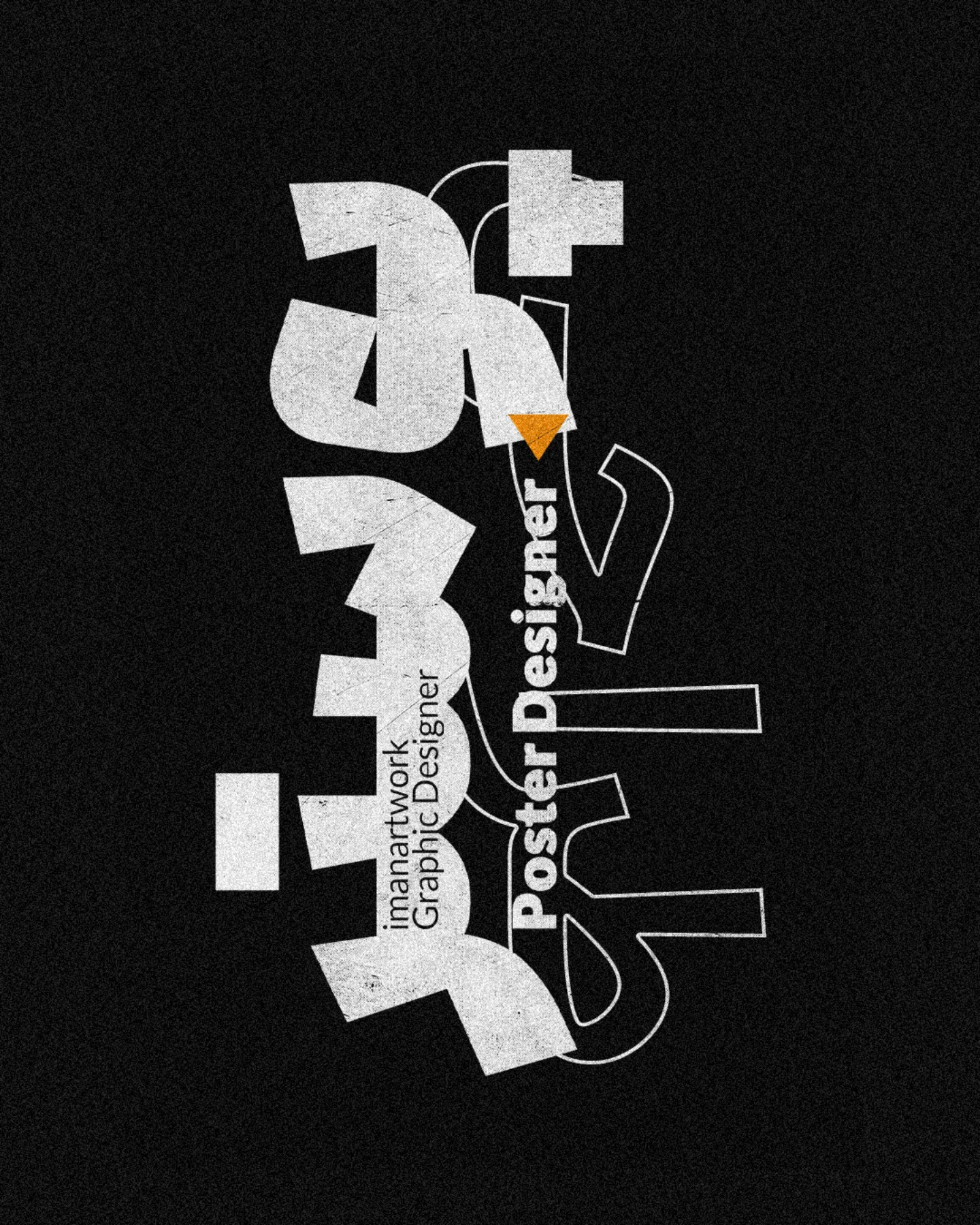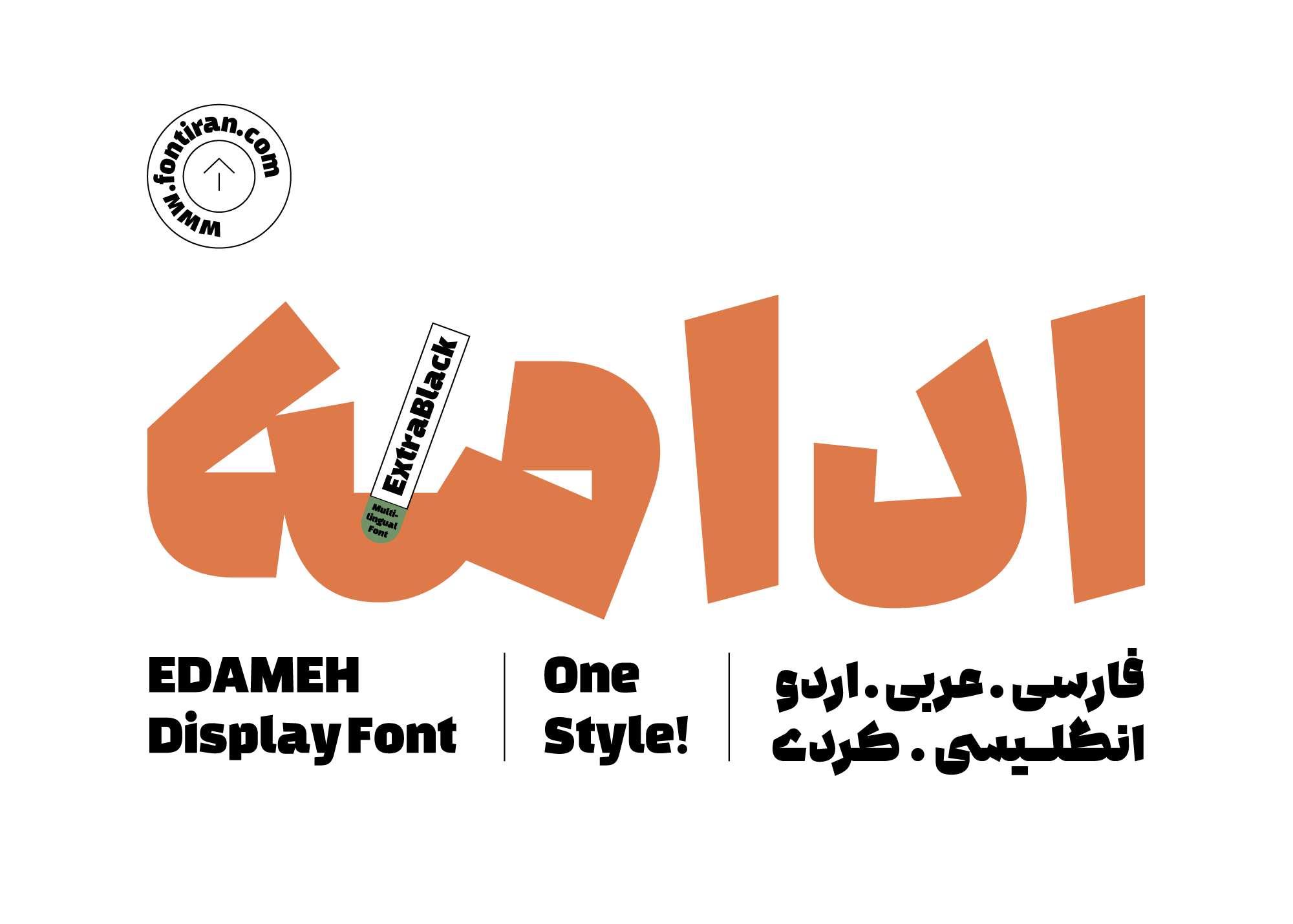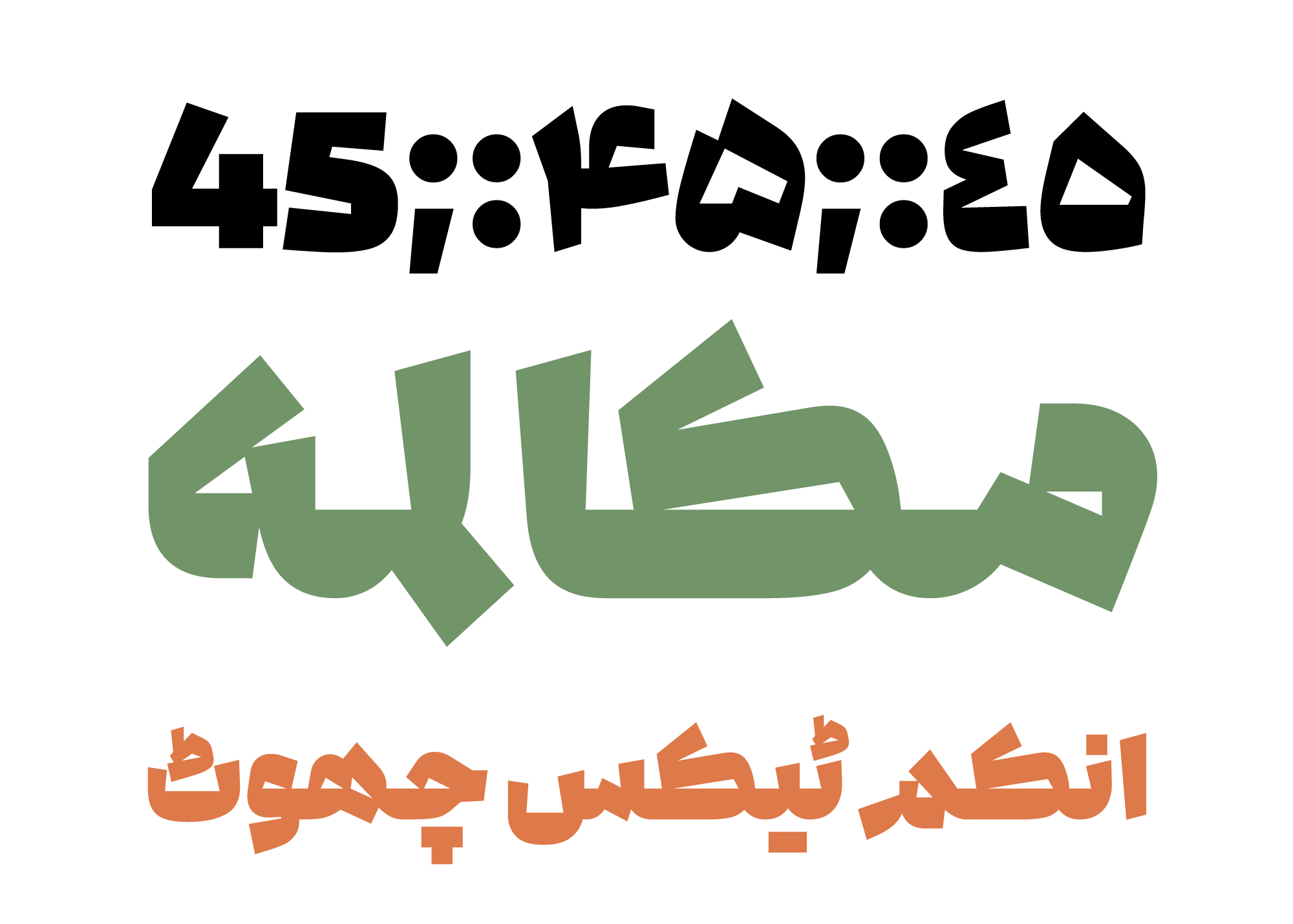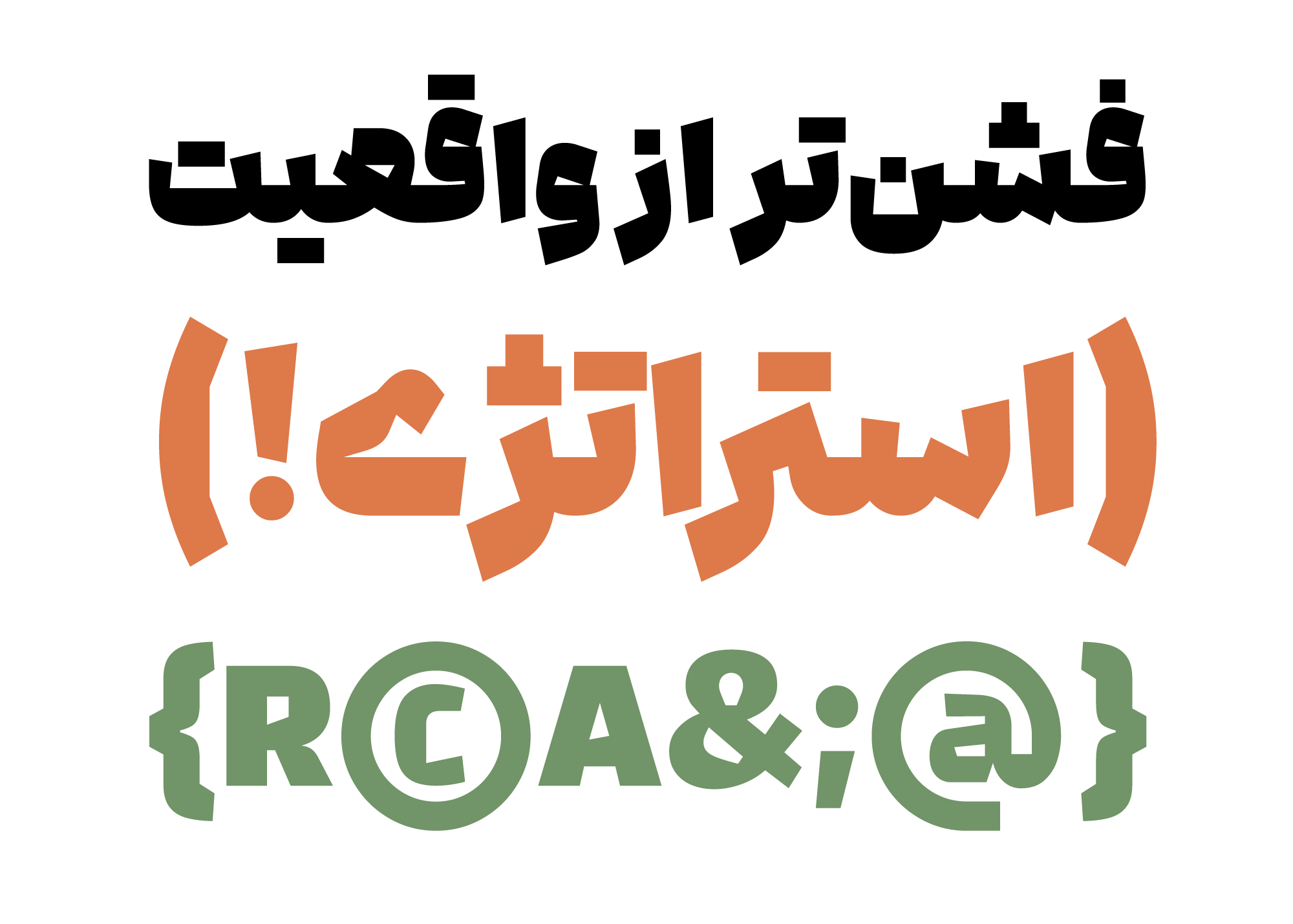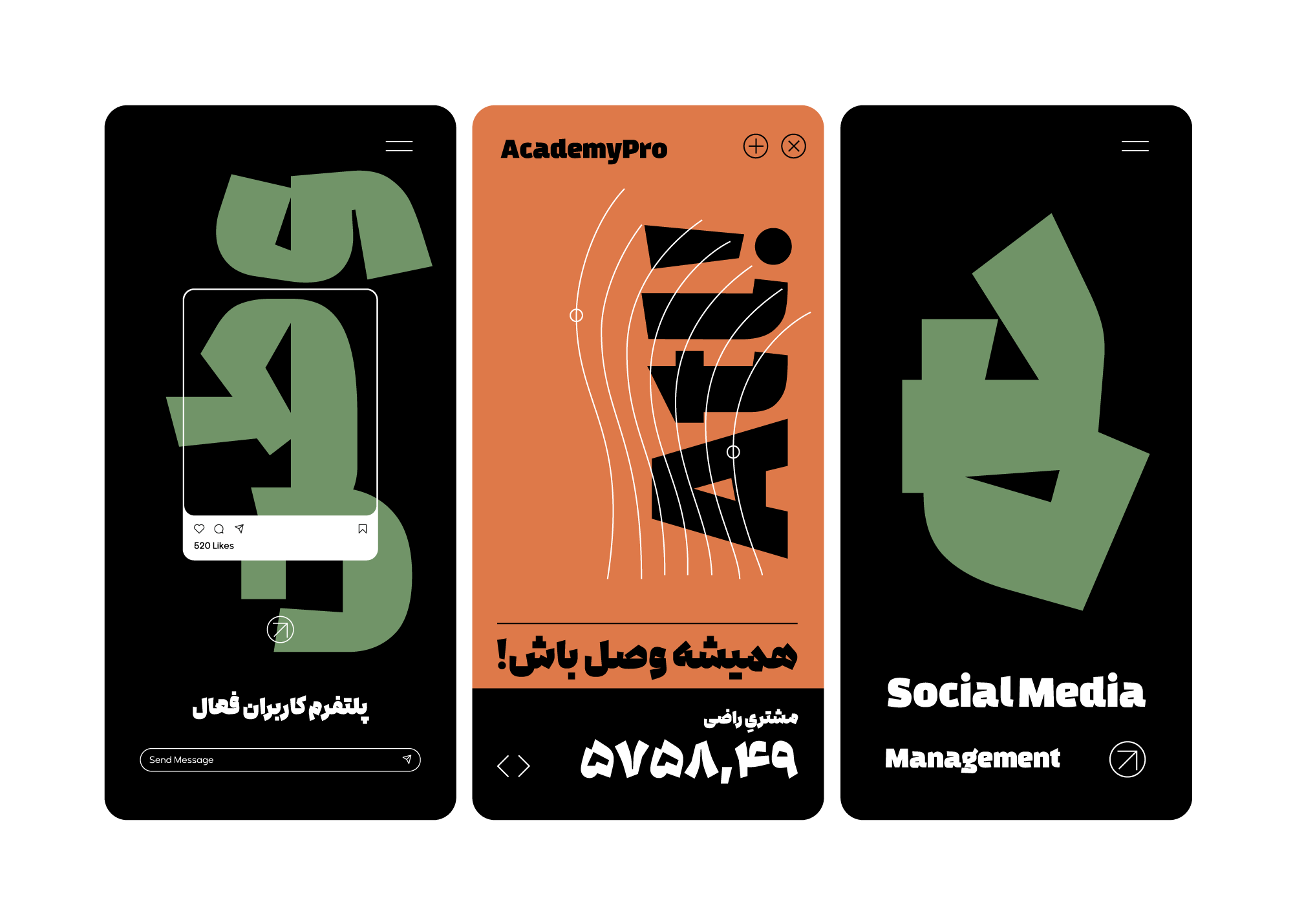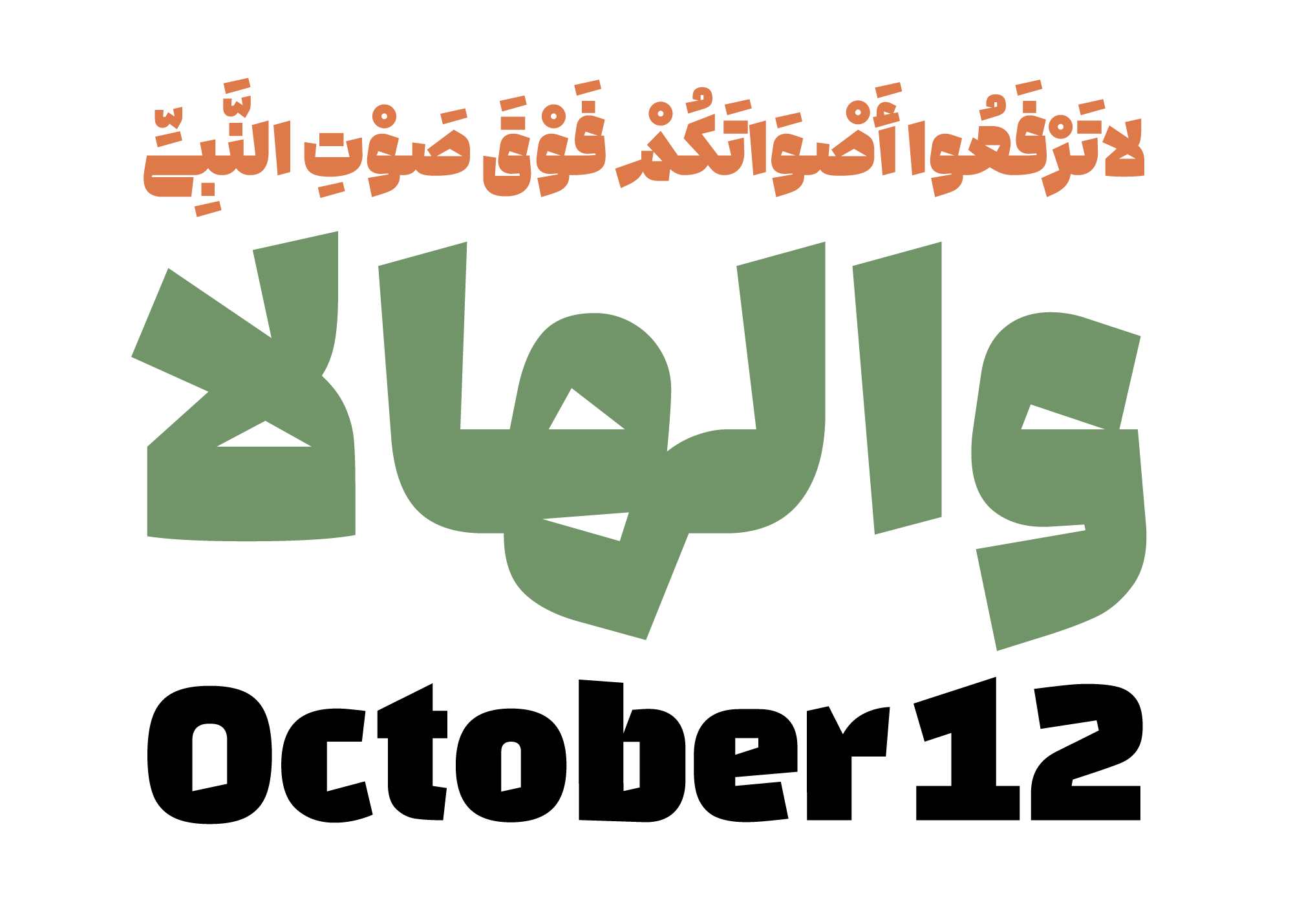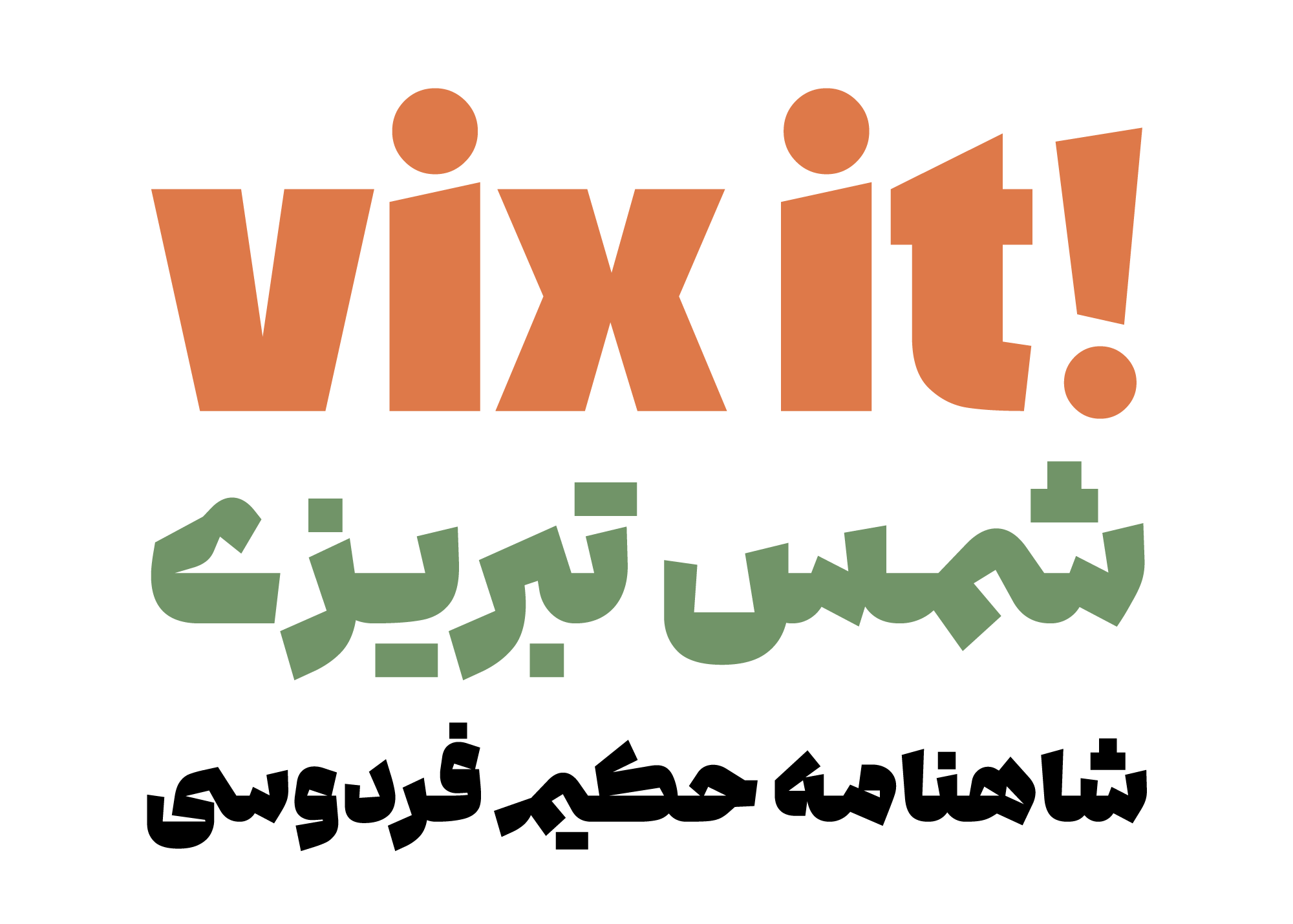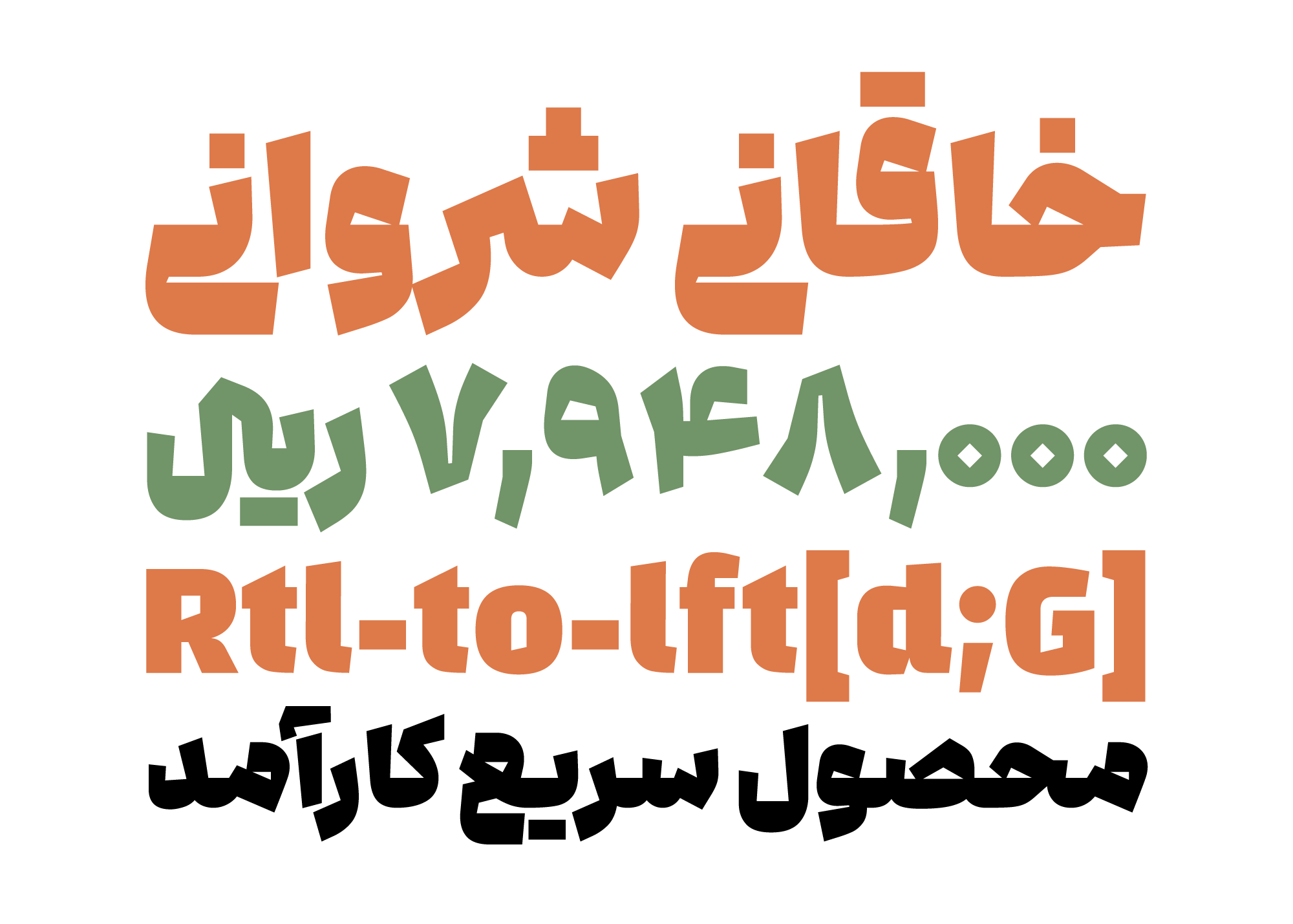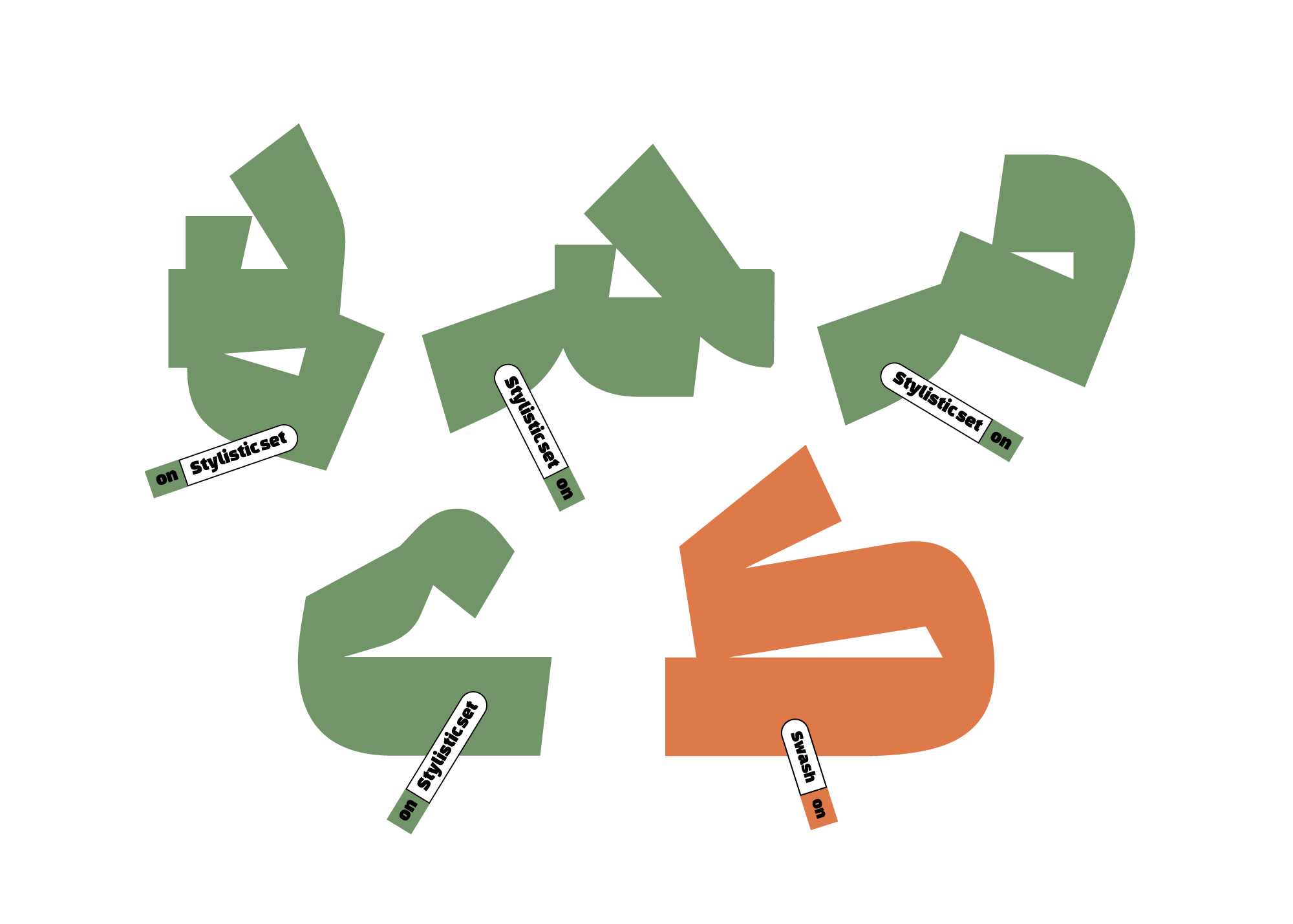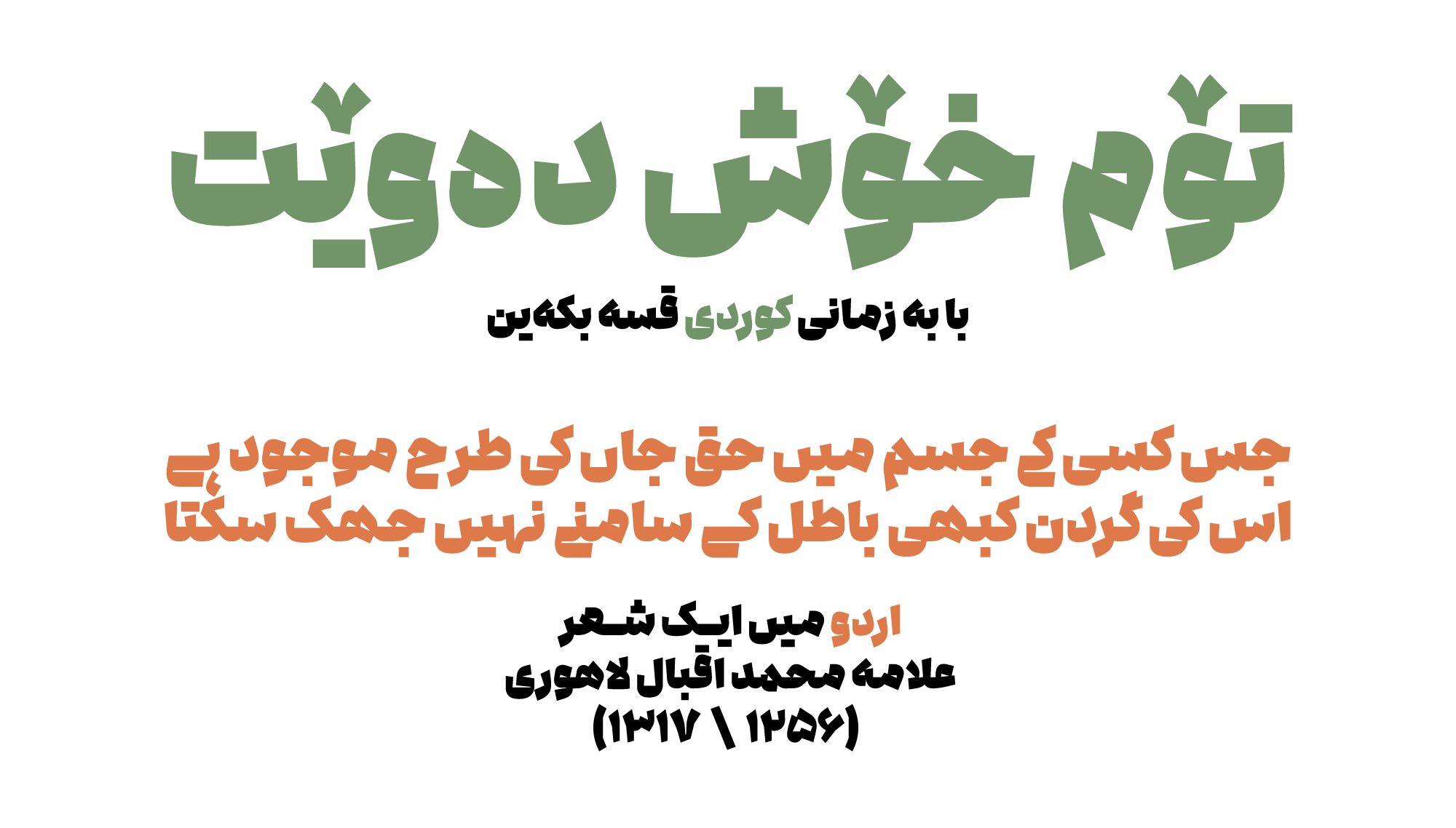
فونت ادامه از زبانهای فارسی، عربی، کردی، اردو و انگلیسی پشتیبانی میکند.
فونت ادامه دارای شخصیتی چندگانه است. گاهی در فرمِ یک حرف، تیزی و خشکی را در کنار منحنی میبینید. اکثر چشمهای حروف دارای فضای منفی مثلثی هستند در حالی که فرمِ حروف مانند مفتول فولادیِ خمیده دیده میشود.
تاکید بر فرمهای چشمگیرِ حروف در عینِ توجه به ظرافتهای طراحی، طراحان و مدیران استارتاپها و بهویژه کسب و کارهای آنلاین را به استفاده از این تایپ در تیتر مطالب خود فرا میخواند.
فونت ادامه دارای اندامی محکم و در عین حال ساده است. این فونت مانند یک تله چشم مخاطب را درگیر خواهد کرد، هرچند اصرار ندارد که خیلی سریع خوانده شود!
اکسترابلک
فونت ادامه، تنها یک وزنِ اکسترابلک دارد. همین کافی نیست؟
حروف و ترکیبات جایگزین
در طراحی فونت ادامه، تعداد زیادی حروف و ترکیبات جایگزین طراحی شده است که میتواند تنوع خوبی در ساختِ تیترها و جملاتِ کوتاه ایجاد کند.
«ک» و «گ» کشیده!
در فونت ادامه میتوانید با فعال کردن Swash در تنظیمات Open Type از حروف جایگزین «ک» و «گ» کشیده استفاده کنید.
حروف جایگزینِ «ی»، «م»، «هـ»
در فونت ادامه میتوانید با فعال کردن Stylistic Set در تنظیمات Open Type از حروف جایگزین «ی»، «م» و «ه»استفاده کنید.
Apply Ligatures
با فعال کردن apply Ligaturs در تنظیمات Open Type ترکیبات جایگزین برای کنترل کشیدگیهای منتهی «ی» فعال میشود.
Discretionary Ligatures
با فعال کردن discretionary Ligatures در تنظیمات Open Type ، ترکیبات جایگزین اتصال دندانهها به «ی» و «ر» فعال میشود.
Discretionary Ligatures+ Stylistic Set1
با فعال کردن dlig و Stylistic Set به طور همزمان در تنظیمات Open Type ترکیبات جایگزین دیگری برای اتصال دندانهها به «م» فعال میشود.
پشتیبانی از زبان عربی و انگلیسی، اردو و کردی
فونت ادامه برای زبان فارسی و عربی طراحی شده است و زبانهای اردو، کردی و انگلیسی را نیز پشتیبانی میکند.
سیّد ناصر خادم، از سال ۱۳۸۷ به عنوان گرافیک دیزاینر و تایپوگرافر فعالیت میکند. تخصص ناصر در انجام پروژههای تایپوگرافی و لوگوتایپ است. وی پیش از این فونتهای کلمه، مدام، پیدا، ادامه، کنار و محال را در وبسایت فونتایران منتشر کرده است.